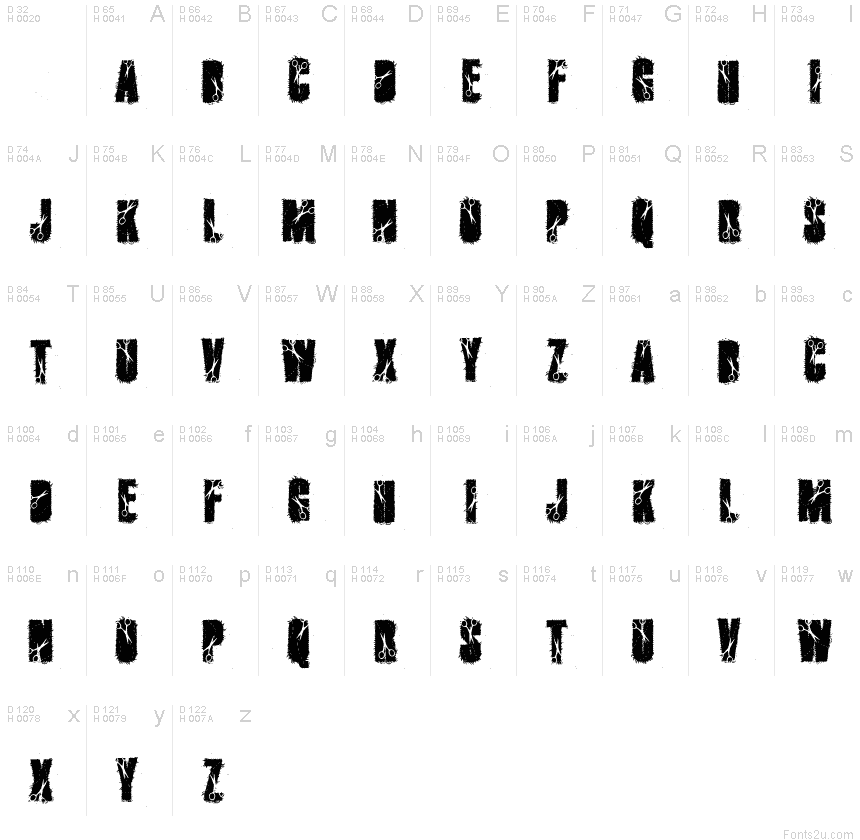
Cutter, von Eric Mynahan, ist eine kostenlose Horror-Display-Schrift mit Zeichen, die aussehen, als wären sie aus Holz herausgehackt und splitternd zurückgelassen worden. Die Großbuchstaben sind schwer, rau und uneben, mit fransigen Kanten, narbenartigen Schnitten und ein paar hängenden, kreisförmigen Einstichen, die dem gesamten Design eine böse, handgemachte Bedrohlichkeit verleihen.
Sie passt perfekt auf Plakate für Slasher-Filme, Flyer für Geisterhäuser, Merchandise für Underground-Bands, Game-Titelkarten und Halloween-Branding. Überall dort, wo diese kostenlose Schrift mit ihrer rohen Art die Stimmung fast alleine erzeugen kann. Verwenden Sie sie für kurze Überschriften, Coverlines oder Monogramme, wenn die Buchstaben zerrissen, erstochen und ein wenig wild wirken sollen.